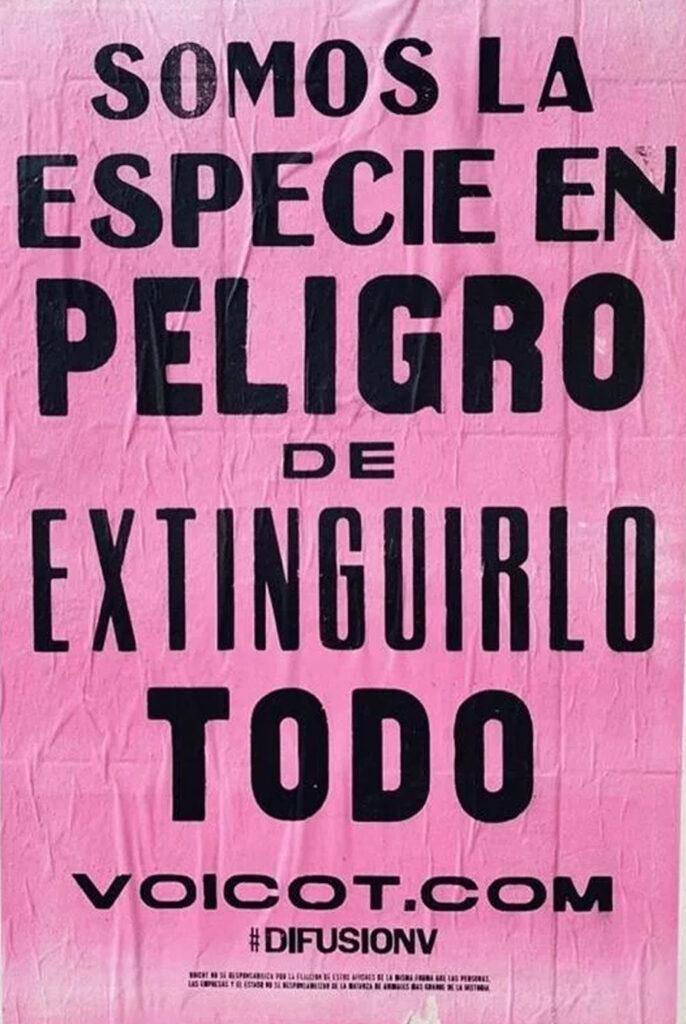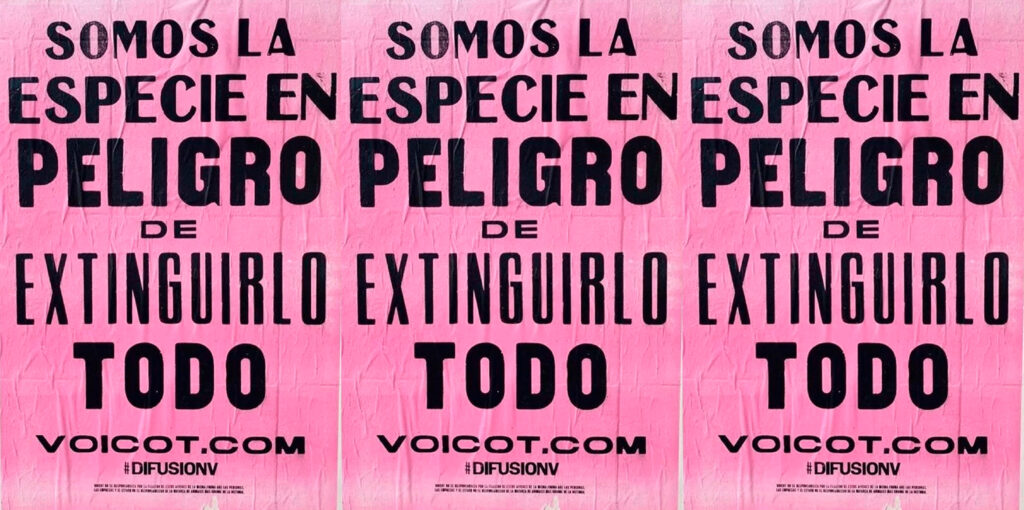
“Empezar a deconstruir lo que nos enseñaron para construir algo mejor para todas las especies que habitamos este planeta”
Voicot es un movimiento artístico por la liberación animal, que usan su creatividad, ingenio y recursos académicos para comunicar un mensaje. Se caracterizan por hacer uso del hiperrealismo, de esta forma logran causar incomodidad, polémica, que se nos revuelvan las vísceras al mirar una realidad que normalmente parece estar oculta a los ojos de todos. Su lucha es muy amplia, y está atravesada por dos ejes principales, el veganismo y la reivindicación de los derechos de los animales como seres vivos, pasando por su impacto ambiental y el desarrollo de economías sostenibles en lugar del consumo masivo que nos caracteriza.
“Chaco es una de las provincias que más grano produce y que más hambre tiene”
Malena Blanco en nota a Infobae
Todo comienza como una iniciativa que brota de la profesión de sus creadores, ellos sentían la necesidad de comunicar un mensaje como publicistas que llegara aún más lejos, poco a poco fueron incursionando en la necesidad de expresar mediante la gráfica, y el uso de medios económicos, para que así el movimiento creciera y se expandiera por sí solo en todos los lugares que calara el mensaje. Dejaron sus productos y afiches colgados en la web para que cualquiera pueda comprarlos, descargarlos e imprimirlos para ser usados a lo largo y ancho de la ciudad, en las calles y en manifestaciones públicas, y así fue como eventualmente las personas hicieron de este movimiento algo personal llevándolo al siguiente nivel. Como dice su co-creadora “ya anda sola”. Y parte de la recaudación es donada a otras organizaciones sin fines de lucro.
La pieza elegida para el análisis es una combinación de estilos modernos y art deco. Su apariencia de elegancia, clase y glamour se muestra como las tendencias visuales de la década de 1920, mezcladas con sans serif geométricas en un enfoque de funcionalidad y estilos completos (Imagen 3°) de familias de fuentes para evitar la monotonía. Se evidencia el uso de Sans Serif con trazos finos y gruesos, que demuestran un rol marcado en cuanto a la estructura de la pieza.
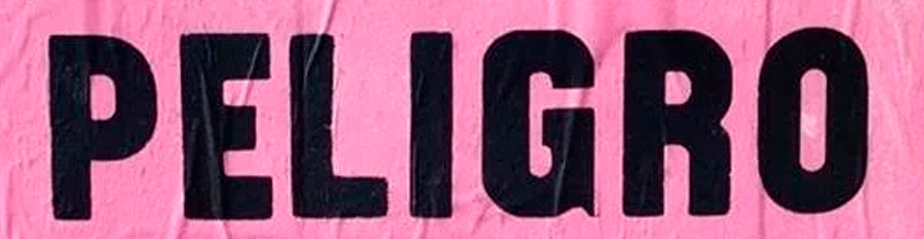
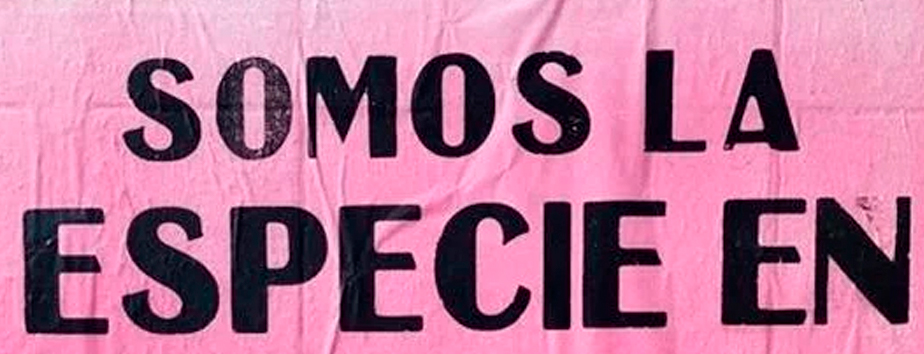
Esto denota la jerarquía de unas palabras sobre otras al usar mayor tamaño y estar destacadas con bold (Imagen 2°), atrayendo la atención del lector y permitiéndole leer fácilmente el mensaje. A su vez podemos determinar 3 niveles de lectura como se observan en la imagen 4°.
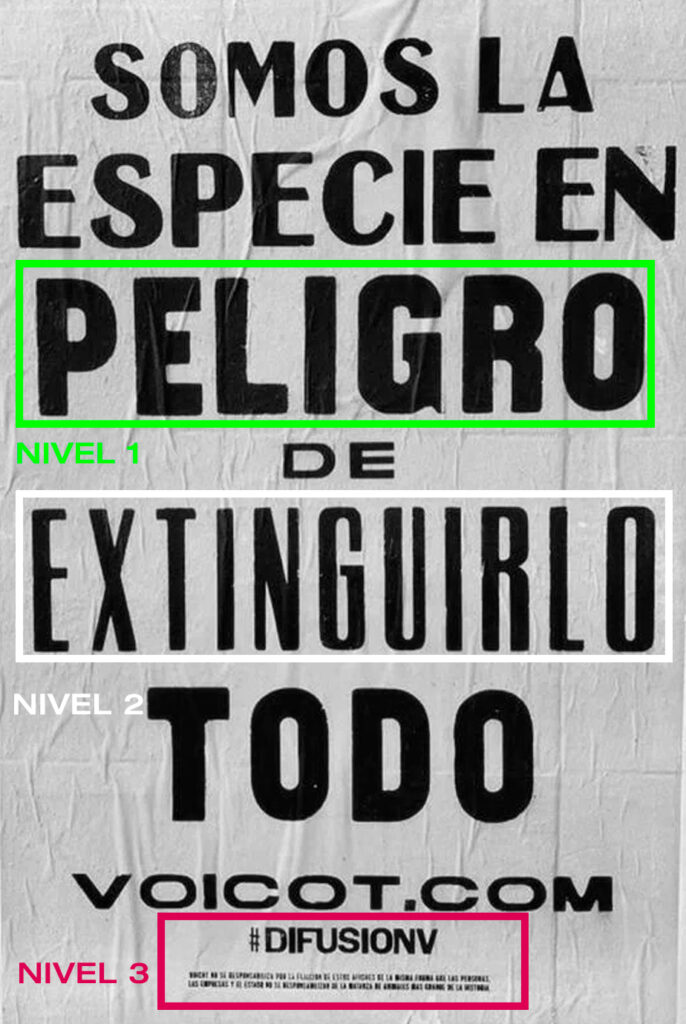
Hay que destacar que la realización de sus afiches son a través de letterpress, lo que condiciona la producción y la composición tipográfica. A su vez le da textura y aspecto desgastado, que es un estilo característico de las luchas sociales.
A grandes rasgos la pieza tiene un recorrido guiado por la jerarquización, tienen palabras más grandes que pretenden entregar un mensaje más rápido y directo. Las demás optan por un tamaño más chico que obliga a detenerse y ver la pieza fijamente para comprender el contexto. Es decir que se toman criterios en base a la funcionalidad de la lectura y el peso de la estructura para poder generar un mensaje rápido y claro.
La pieza está formada por un fondo color rosa y la tipografía siempre de color negro ocupa casi la totalidad de la página. Esto debido a que la tipografía responde al formato comunicativo y al objetivo final del mensaje. De la misma manera se observa que los márgenes son casi nulos, el contenido llega hasta el borde la pieza, sin espacios, excepto el generado por las mismas palabras y la interletra.
“Voicot no se responsabiliza por la fijación de estos afiches así como las personas, las empresas y el estado no se responsabiliza de la matanza de animales más grande la historia.”
En conclusión respecto al uso de estas expresiones gráficas en conjunto con el movimiento podemos destacar la utilización limpia de las tipografías para llamar la atención de los simpatizantes que puedan apoyar la causa y sobre todo el uso de los afiches y la representación gráfica visceral para darle voz a todos los que no pueden hablar.